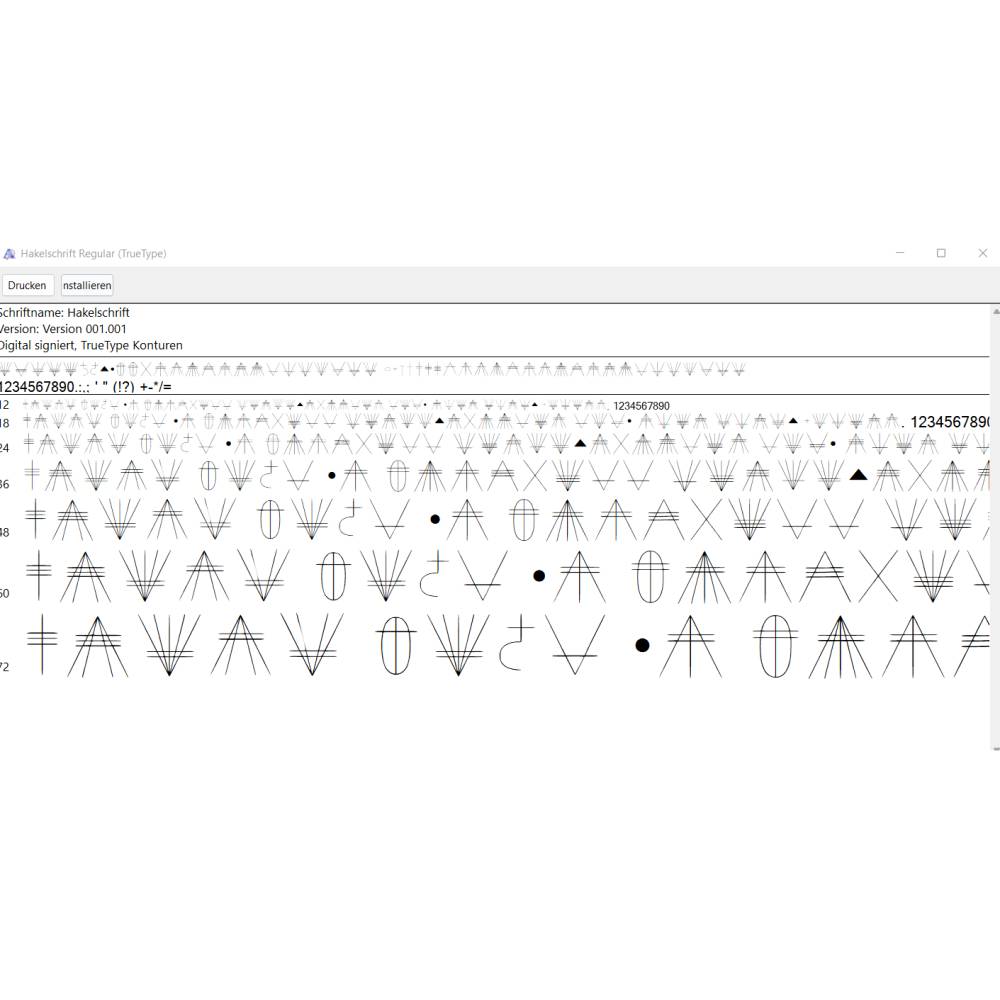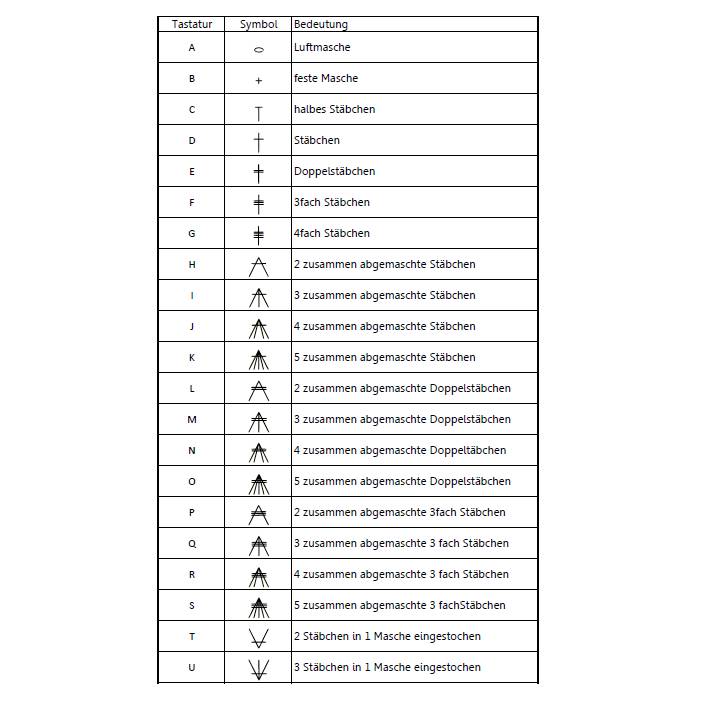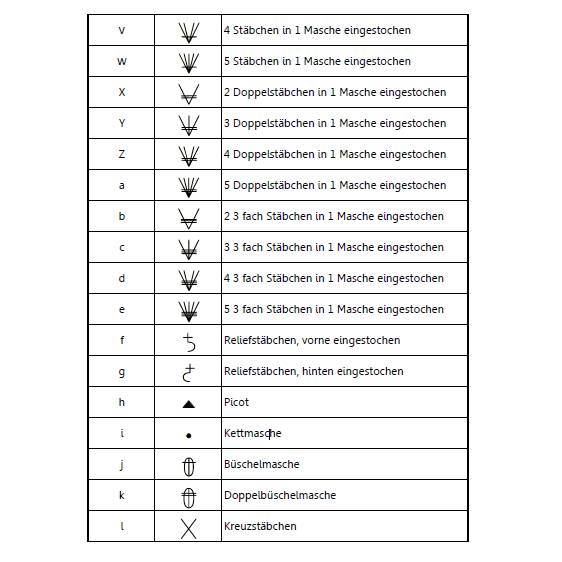
Häkelschrift, digitaler Font, Satzschrift zur Erstellung von Häkelanleitungen
Der Font ist bestens für alle kreativen Häkeldesigner geeignet, die ihre eigenen Anleitungen erstellen.
Die Zeichen sind nach gängigen Standard definiert, können aber zu jederzeit nach dem eigenem Bedarf in der Bedeutung angepasst werden.
Auf den Fotos sieht man, welche Symbole enthalten sind mit der entsprechenden Tastaturbelegung.
Die Zeichen erscheinen beim Schreiben etwas kleiner als normale Buchstaben und die Schriftgröße sollte etwas größer eingestellt werden.
Sie kann außerdem auch in fett, kursiv oder unterstrichen ausgewählt werden.